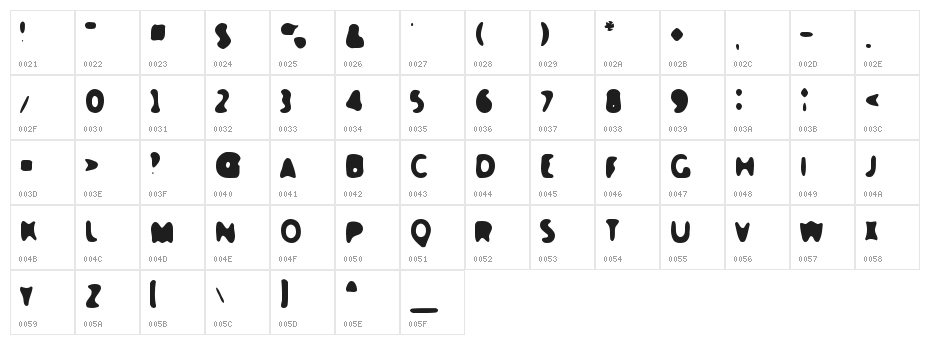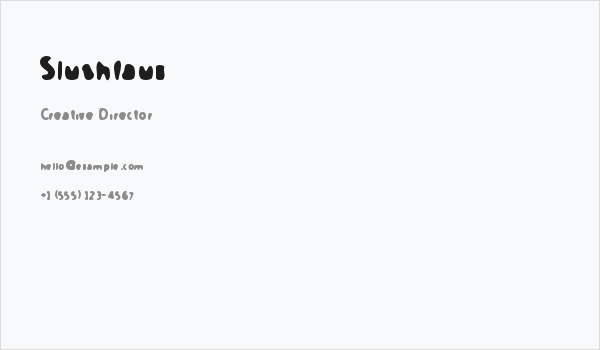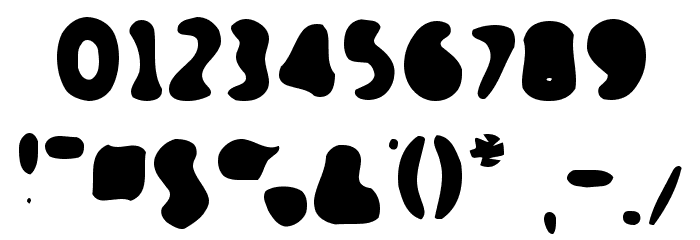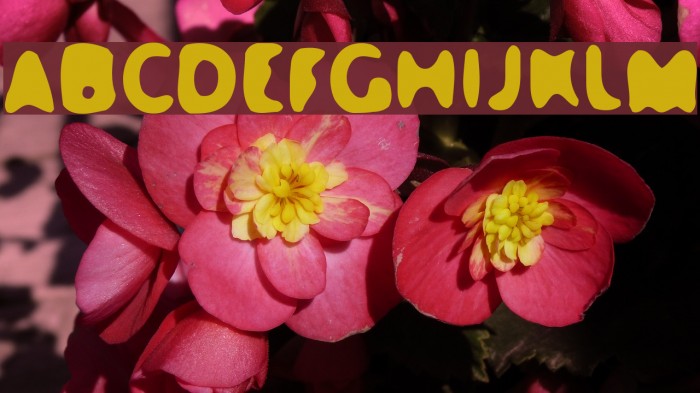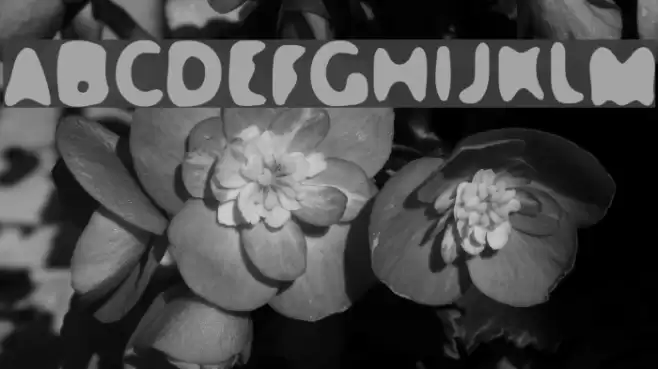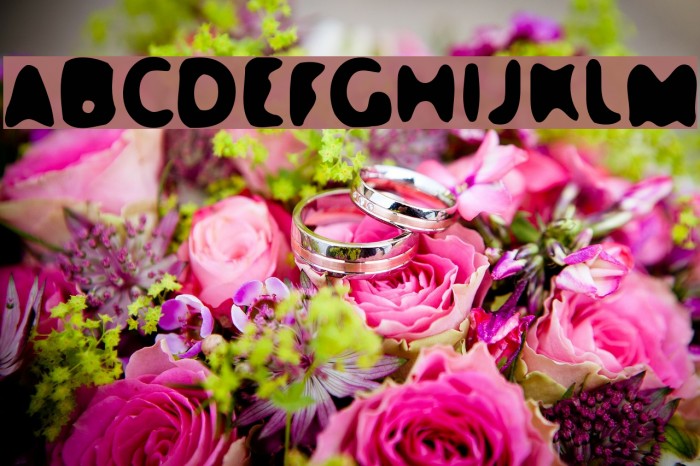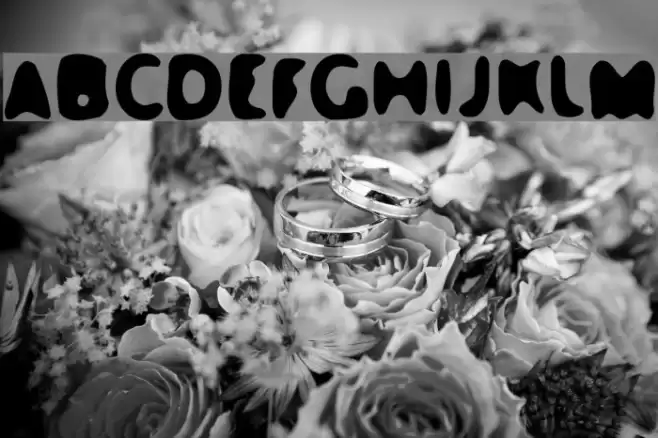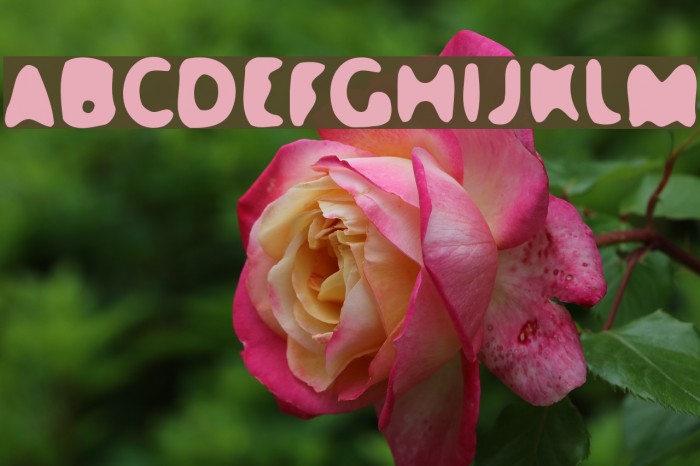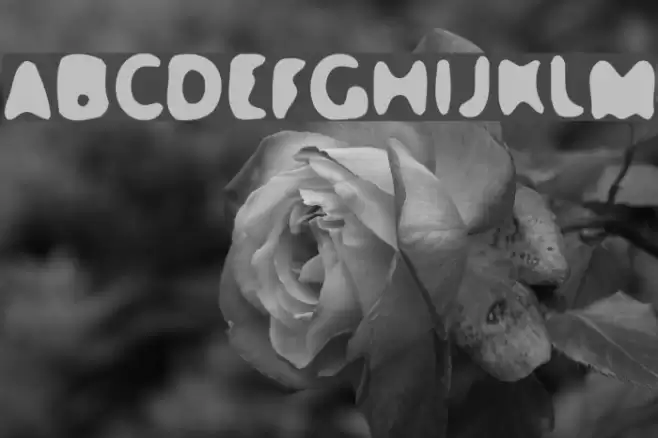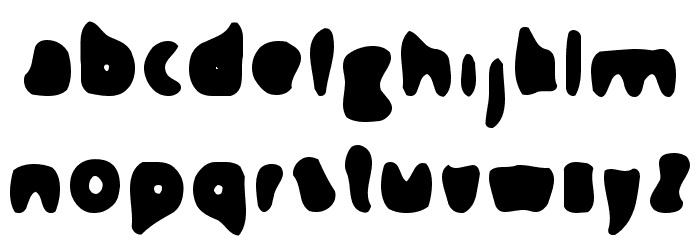
Slushfaux Font
| Общий стиль | Playful, Whimsical |
| Рекомендуемые проекты | Ideal for children's books, playful branding, creative posters, and any project needing a fun, informal touch. |